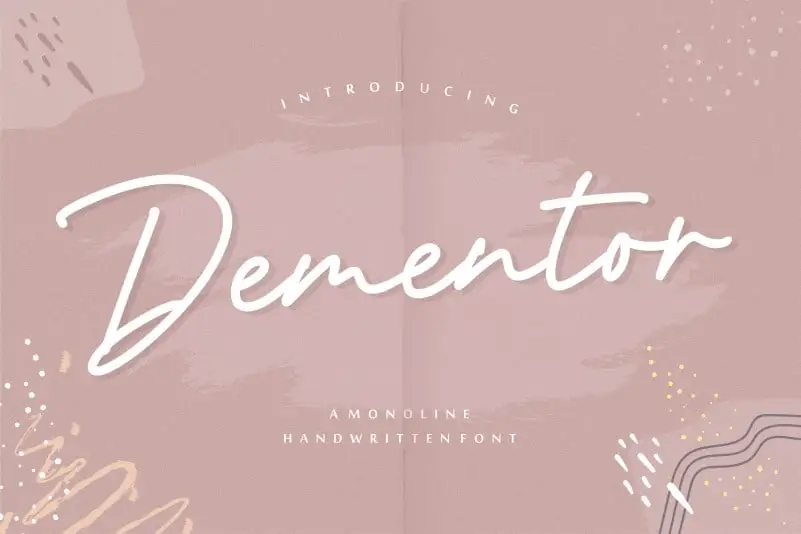
Dementor Handwritten Font – Download Grátis
A Dementor Handwritten Font é a escolha perfeita para designers que buscam uma fonte elegante e única para expressar sua personalidade nos projetos mais inusitados. Suas linhas suaves e desenhadas com cuidado proporcionam um toque autêntico em qualquer projeto, seja para embalagens de produtos, identidades visuais de marcas, revistas e editoriais, perfis nas redes sociais ou até mesmo gráficos de anúncios de casamento. Suas características fluidas permitem que você use a fonte para destacar mensagens importantes ou expressões sutis que se sobressaem no contexto do projeto. Com sua capacidade de ser tanto elegante quanto criativa, a Dementor Handwritten Font oferece aos designers uma opção versátil e impecável para quando se trata de fazer letras soar de maneira única. Ideal para qualquer aplicação onde você deseja destacar seu texto em meio a um fundo ou como parte de sua identidade visual. Seja em uma campanha de marketing, projeto editorial ou até mesmo gráficos pessoais, esta fonte é certamente capaz de fazer seu trabalho soar ainda mais singular e memorável. Ao escolher a Dementor Handwritten Font, você não só recebe um recurso visual excepcional, mas também contribui para manter o design no Brasil atual sempre imbuído de criatividade e estilo.